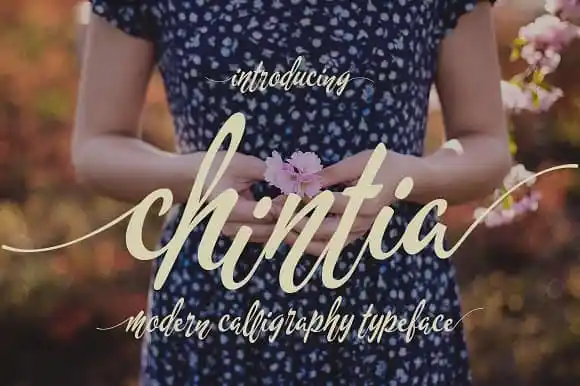
Chintia Script Font – Download Grátis
A Chintia é uma fonte de calligrafia à mão que transmite uma sensação natural e suave, perfeita para quem procura personalizar qualquer projeto de design. Com seu estilo moderno e ondulado, essa fonte foi criada especificamente para atender às necessidades de projetos de design futuros. Ideal tanto para criação de logotipos quanto para incorporar em cartões de visita ou cartazes de nome, a Chintia oferece uma versatilidade impressionante. Suas linhas suaves e sua estrutura clean tornam-na perfeita não apenas para assinaturas e cartões personalizados, mas também para pacotes de produtos, marcas de marca, maquetes de cabeçalhos e qualquer outro projeto onde você possa imaginar usar. Seja qual seja o seu próximo design, a Chintia atende ao seu requisito perfeitamente.